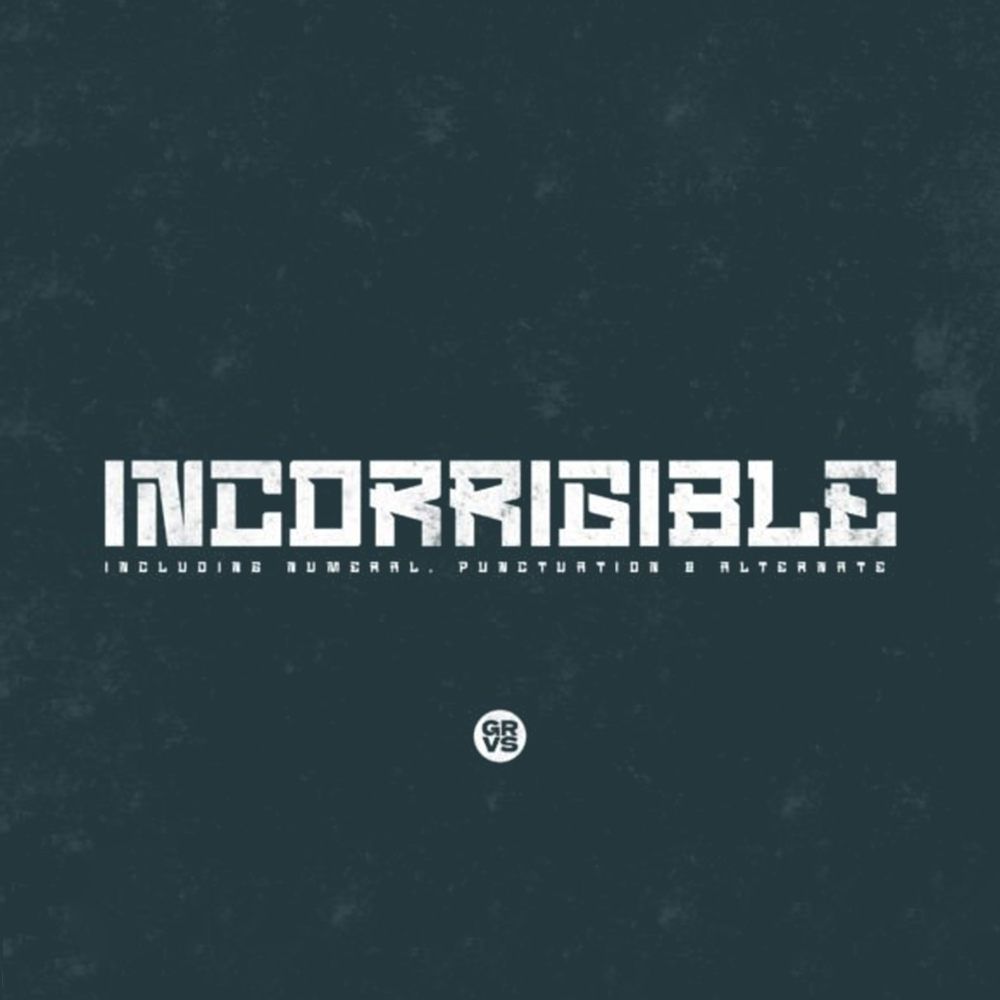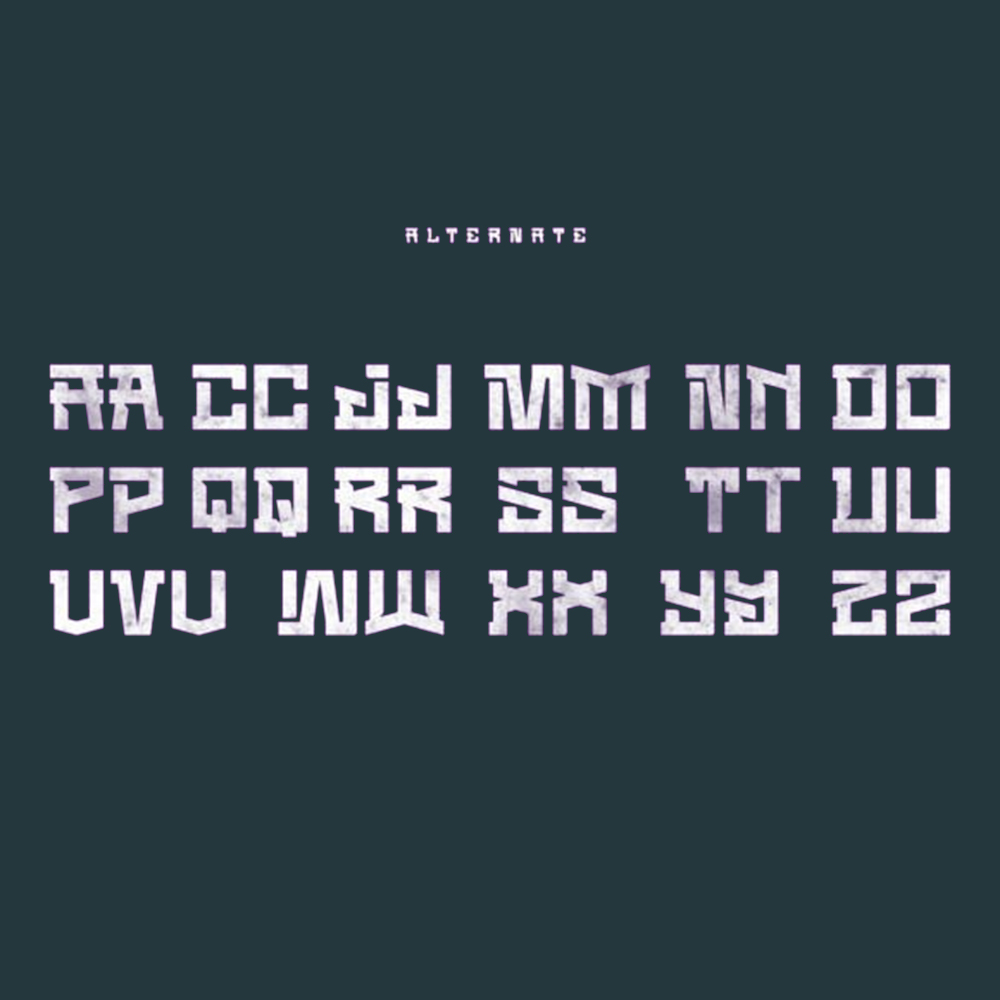
دانلود فونت انگلیسی Incorrigible Font
فونت پرمیوم و انگلیسی Incorrigible Font محصول جدید ماست که برای کسب و کار یا لوگوی شما با موضوع بازی و ورزش، لوگو، استیکر، پیراهن، کارت دعوت، بروشور و غیره مناسب است.
مزایای استفاده از فونت لاتین Incorrigible Font چیست؟